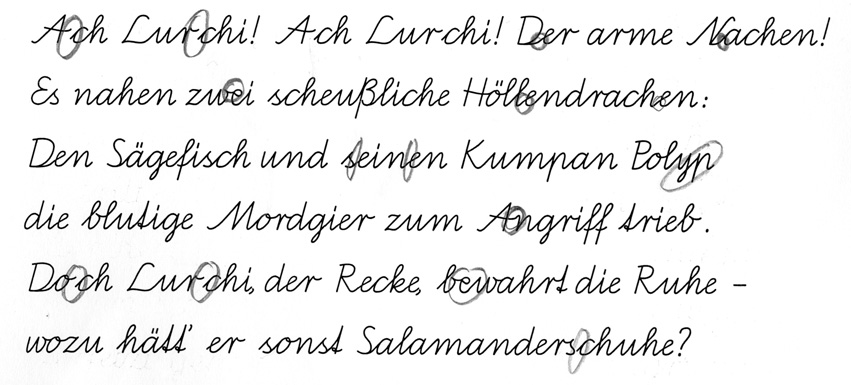
Ich habe eine Handschrift digitalisiert, und möchte zu diesem Zweck Alternative Glyphen einstellen, um eben den handschriftlichen Stil zu unterstützen.
Habe aber leider keine Ahnung wie.
Ganz grob umrissen (im Detail ist es ziemlich viel um mal eben zu erklären ...):
Du möchtest eine Opentype-Schrift erstellen, und zwar mit kontext-sensitiven Ersetzungen (das Opentype-Feature CALT) und ggf. Ligaturen (LIGA). Damit kriegst du schon einen ziemlich handschriftlichen Eindruck, auch wenn es noch ausgeklügeltere Systeme gibt (mehrere Varianten der Reihe nach durchspielen, etc.).
Ein Beispiel für diese Methode hier (oben ohne Ersetzungen, unten mit):
D.h.: wenn im Text z.B. ein "ei" vorkommt, soll stattdessen die Ligatur "e_i" angezeigt werden.
Dafür musst du zum einen die Glyphe "e_i" anlegen, und dann im Opentype-Feature LIGA eine Ersetzung veranlassen:
feature liga {
sub e i by e_i;
... weitere Ersetzungen ...
} liga;
Wenn am Ende eines Wortes ein Buchstabe einen Abschwung haben soll (z.B. ein ausschweifendes e), dann legst du eine Glyphe e.ende an, und erstellst dann das Feature calt:
feature calt {
sub e' space by e.ende;
... weitere Ersetzungen ...
} calt;
Ligaturen habe ich schon (massenweise) eingesetzt.
Aber die Variante für Buchstaben an Wortenden hilft mir auch schon.
Zusatz:
Das ganze geht natürlich nicht nur am Wortende, sondern überall:
sub s c' h by c.alt;
ersetzt z.B. das c in der Zeichenkombination "sch" durch eine alternative Form c.alt
Wenn genug solcher Varianten eingestreut werden, und diese nicht zu auffällig sind und damit in der Wiederholung unschön hervorstechen, kommt man damit schon sehr weit.
Es gibt inzwischen auch ausgefeiltere Logiken, z.B. für jeden Buchstaben 4 Varianten, die dann alternierend oder pseudo-zufällig eingesetzt werden (die Neuauflage der Schreibmaschinenschrift FF Trixie macht das z.B. um ein unregelmäßiges Schriftbild durch leichte Variation zu erzeugen). Ob die Hersteller die Methoden rausgeben, bezweifle ich zwar, aber ich meine, dazu schon mal was auf typophile.com gelesen zu haben.
Das hier vielleicht?
Das so zu implementieren ist schon sehr hässlich (und aufwendig und damit fehleranfällig). M.E. wird da die »calt«-Funktion missbraucht, um Zufälligkeit vorzutäuschen. Kontextbezogenheit soll ja gerade nicht zufällig sein. Konzeptionell korrekt wäre natürlich der Einsatz der »rand«-Funktion (ggf. in Verbindung mit Ligaturen, Swashes, »calt«, »fina« etc. pp.), aber da soll es wohl an Softwareunterstützung mangeln (was aber nun bei OpenType generell nichts neues wäre).
Ist aber auf alle Fälle spannend. :cheer: Ich muss das demnächst mal ausprobieren, ob sich mit FontForge+XeTex da irgendwas machen lässt.
Ich habe es noch nicht ausprobiert (Asche auf mein Haupt) - aber es scheint ja zu funktionieren...
Ich muss das demnächst mal ausprobieren, ob sich mit FontForge+XeTex da irgendwas machen lässt.
Bei XeTeX gibt's nur ein kleines Problem: Ersetzungen über Wörter hinweg funktionieren nicht, weil XeTeX die Wörter abgetrennt behandelt.
Na dann funktionieren diese komplizierten »calt«-Regeln nicht so wie gedacht. Schade, aber mein Argument war ja ohnehin, dass »calt« m.E. zweckentfremdet benutzt wird, um den Anschein von Zufälligkeit zu erwecken. Bei »rand« sollte aber die Wortgrenze kein Problem darstellen. Aber ich habe im Moment keine Ahnung, ob das überhaupt unterstützt wird.
Danke für den Link, ja der war's.
Wenn man da weiter nach unten liest, finden sich auch Lösungen für Wort-übergreifende Wiederholungen, und soweit ich das verstanden habe (ich hab's nie ausprobiert) zumindest auch eine theoretische Methode, nicht einfach alle Buchstaben durchzuzählen und danach zu wechseln, sondern tatsächlich jeden einzelnen Buchstaben für sich zu wechseln. Das scheitert nur an der Maße an Anweisungen und Klassen, sowie der Performance der Satzsoftware bei der Umsetzung.
RAND wäre dafür das richtige Feature, ist aber nirgends implementiert, somit eine theoretische Sache.
SALT wäre auch passender als CALT, ist aber nur in Illustrator, Photoshop und xPress implementiert, nicht in Indesign (ob sich da in Version CS5 was getan hat, weiß ich aber nicht).
CALT hat den Vorteil, dass es standardmäßig aktiv ist - die meisten Anwender spielen ja nicht wirklich mit den Opentype-Features rum, sondern nutzen die Voreinstellungen ...